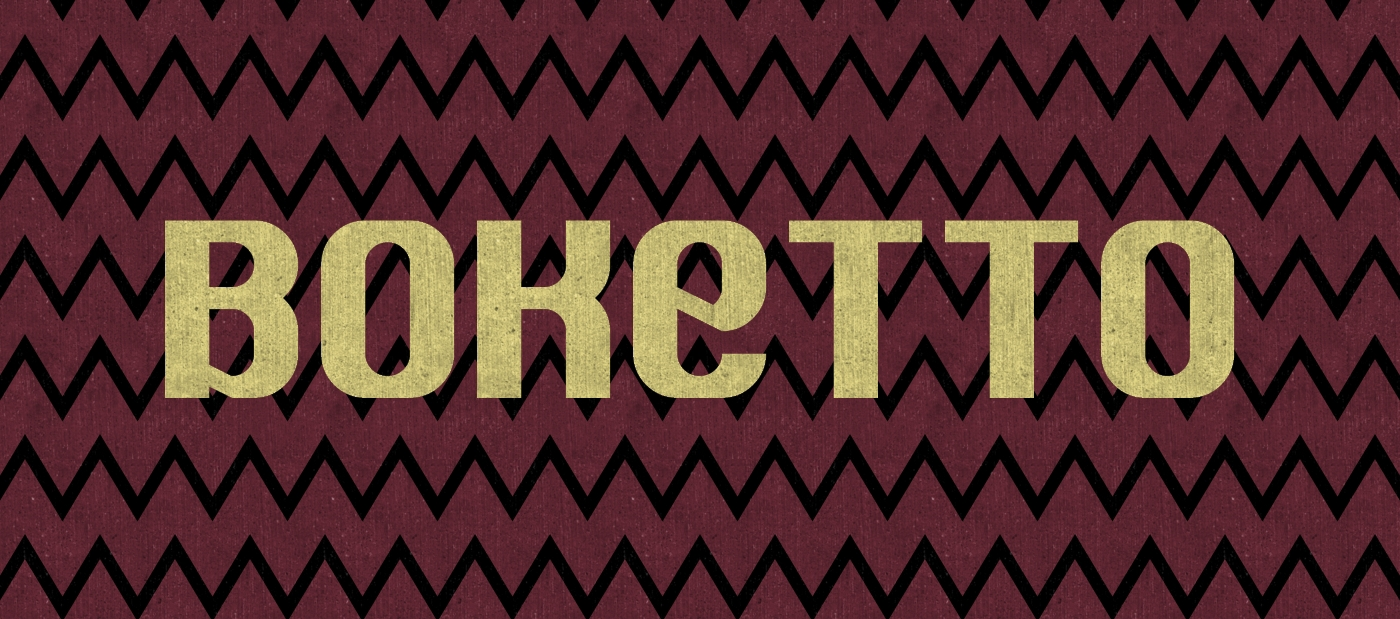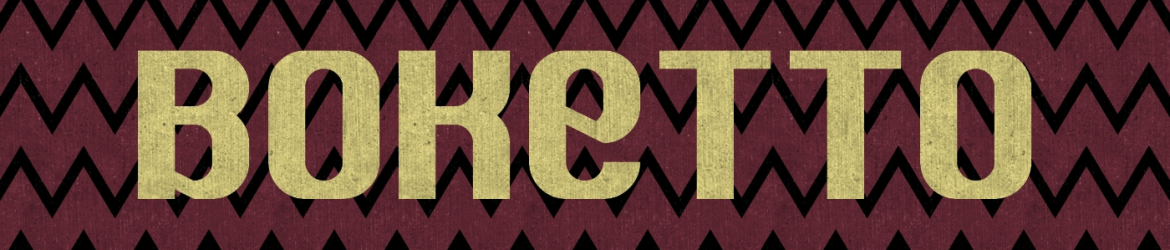
A Boketto Font é uma tipografia sans-serif que remete às atitudes distraídas dos japoneses quando olham para longe sem pensar. Inspirada no vocabulário japonês, especialmente no termo “boketto”, que descreve o gesto de ficar imóvel, fixando a atenção em algo distante como uma distração ou uma atividade mental inativa. Essa fonte é um belo exemplar do estilo sans serif, ideal para criações gráficas contemporâneas e modernas. Seu designer, Hamilton, cuidadosamente criou essa tipografia de modo que seja fácil de ler em qualquer formato visual, desde sites até materiais impressos. A Boketto Font não apenas atende à exigência da categoria sans serif fonts, mas também oferece uma conexão cultural única através do termo inspirador que dá nome a ela. Se você está procurando por uma fonte moderna e versátil, sem dúvida esta font será um escolha perfeita para seus projetos digitais.